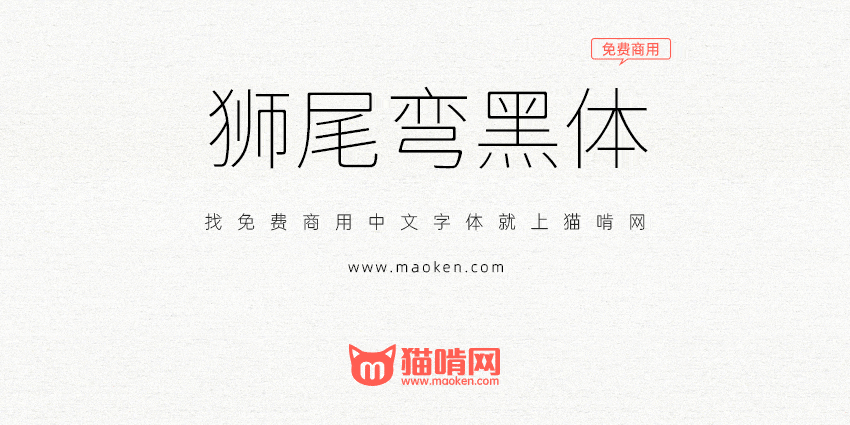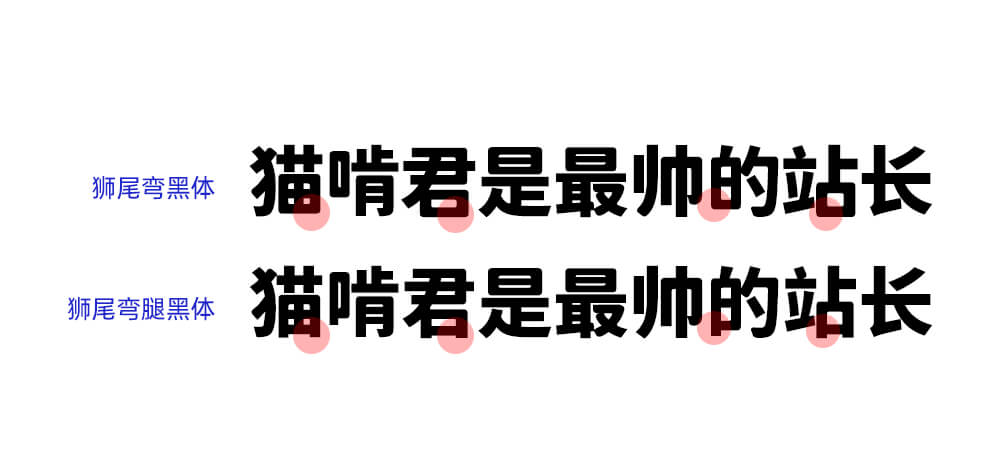
字体作者:Max(中国台湾) | 字体字重:7个 |
狮尾弯黑体基于思源黑体的变圆和拔脚改造,更加简明现代化的字体。支援简体中文、繁体中文、韩文与日文;可以免费商用,欢迎大家自由应用、自由优化、自由改作!
「狮尾弯黑体」与「狮尾圆体」的主要差别在笔触是否有做调整,狮尾弯黑体所套用的效果较少,在笔触没有做调整。